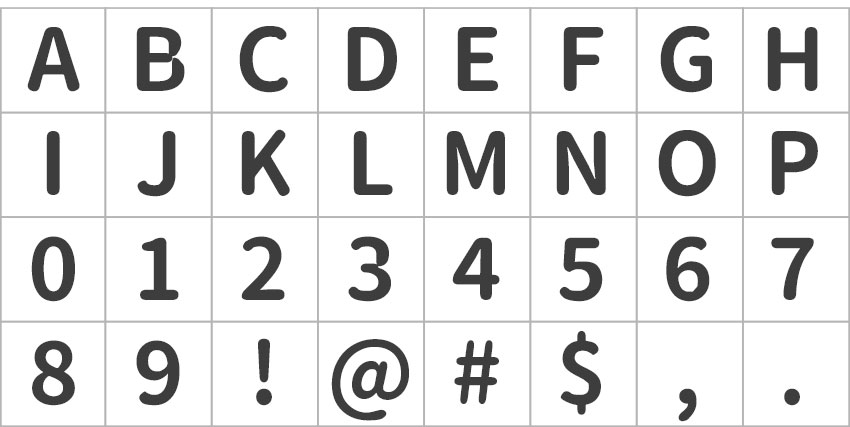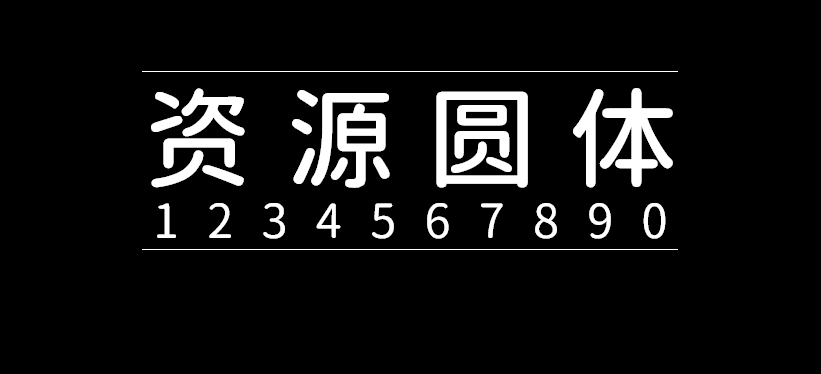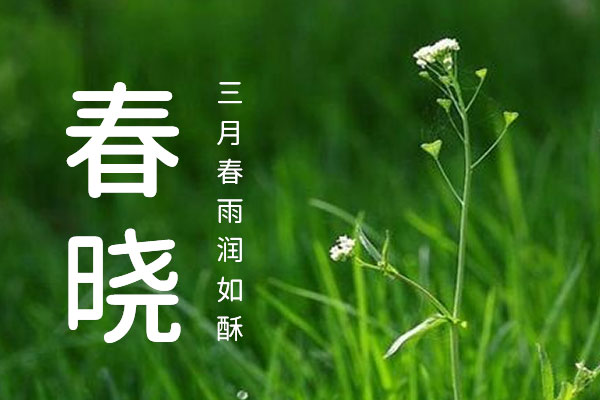
资源圆体
说起可以免费商用的圆体字型,大家可能都会想到源柔黑体(国内网站上都叫“思源柔黑”),现在继续推荐另外一款字体:资源圆体。资源圆体是国内设计师Cyano Hao基于中国版的思源黑体改造而成的圆体字体。 资源圆体(Resource Han Rounded)是思源黑体的直接变圆版,所以它的特征跟思源黑体基本上是一样的,所以资源圆体对简体支持十分好!简体不缺字!而且资源黑体和思源黑体一样,拥有7个字重!基本满足了大部分的设计需求。资源圆体是依据SIL Open Font License 1.1授权协议,可以用于任何用途,包括免费商用。